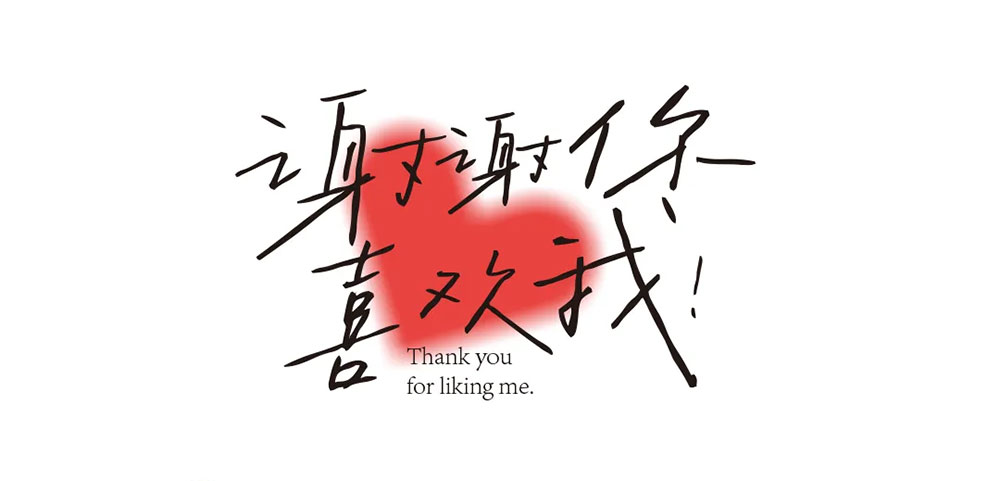
字制区喜脉喜欢体
喜脉体发布以来,出乎意料的受到各界欢迎,央视TV、奥运会、BAT、字节、小红书、各大明星电视机、还有平时逛超市货架上的商品上均有展露,就连到朋友开的咖啡店都看到杯套上用的是喜脉体................,也许这就是普通人的自豪感。
去年,在练习iPad手写的时候,想着要不索性写一套拙字吧,好看的写不出,但自然文艺有温度的还是可以试试的。
于是我借鉴两款市面上已发布的手写体,进行了两者风格的结合,但最终写了一套今天要送给大家的这份礼物,它叫——字制区喜脉喜欢体。
字体风格比较文艺、自由,比较适合作为字数少的大标题使用,像自媒体封面标题/字幕、音乐专辑、电影海报、杂志、照片排版等,都是非常匹配的场景哦!